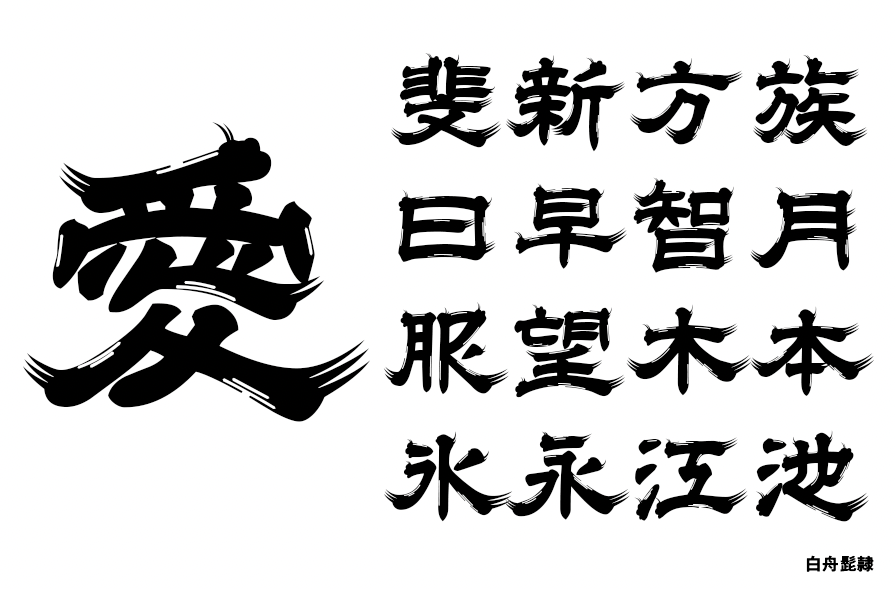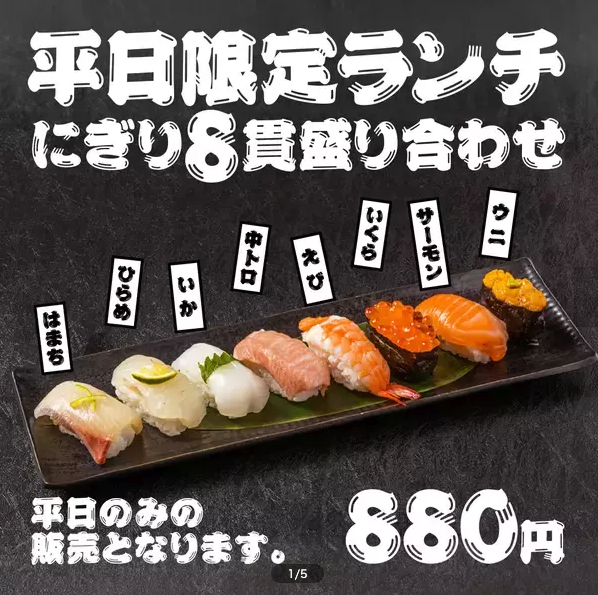
髭文字(ひげもじ)是日本江户时代所使用的广告字体之一。
由粗刷绘制,和寄席文字、篭文字一样属于灰度很重的字体。其特点是在笔画末端带有须状的装饰,类似中国书法的飞白,并且在笔画内部有类似高光的装饰。这种字体的名称来源于其独特的笔画特征,看起来像是长了胡须一样。
在江户时代,髭文字被广泛应用于各种广告和宣传材料中,如招牌、海报、传单等,以吸引顾客的目光。
在现代,髭文字以其优秀的夺目性依然被设计师们所喜爱,它不仅出现在传统的广告设计中,还被应用于现代的品牌标识、包装设计、网页设计等领域。设计师们通过创新和演变,将髭文字的传统元素与现代设计理念相结合,创造出既具有传统韵味又不失现代感的作品。